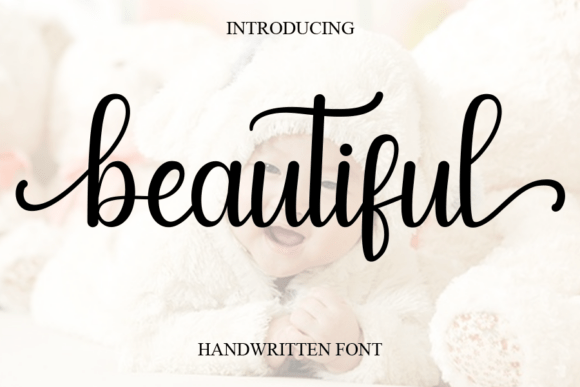
Beautiful
Beautiful – La police manuscrite qui allie élégance et convivialité
Vous cherchez la typographie idéale pour sublimer vos projets créatifs ? Beautiful est une police douce, cursive et manuscrite qui apporte une touche joyeuse et romantique à chaque design. Que ce soit pour du branding, un logo, un faire-part de mariage ou une campagne marketing, elle se démarque par son style à la fois raffiné et décontracté.
Pourquoi choisir Beautiful ?
- Aspect élégant et détendu : ses courbes fluides offrent une allure sophistiquée sans être trop formelle.
- Polyvalence exceptionnelle : parfaite pour le branding, les logos, les invitations de mariage, les cartes de vœux, les lookbooks mode, les promotions marketing, etc.
- Facile à lire : malgré son style manuscrit, chaque caractère reste clair, ce qui garantit une excellente lisibilité même en petite taille.
- Ambiance romantique : ajoute instantanément une sensation de chaleur et de proximité, idéale pour des projets où l’émotion compte.
Idées d’utilisation concrètes
- Création de logos haut de gamme pour des marques de mode ou de beauté.
- Conception de faire-part de mariage, d’invitations et de cartes de remerciement.
- Design de cartes de vœux et de papeterie personnalisée.
- Réalisation de lookbooks, catalogues et affiches promotionnelles.
- Intégration dans des campagnes publicitaires digitales pour un rendu chic et chaleureux.
Conclusion – Un choix sûr pour un rendu chic et décontracté
En résumé, Beautiful est la police manuscrite qui combine parfaitement élégance et casualité. Elle donne à vos créations une allure sophistiquée tout en restant accessible et chaleureuse. Que vous soyez designer professionnel ou amateur passionné, cette police deviendra rapidement votre alliée favorite pour tous vos projets où le raffinement et la douceur sont de mise.